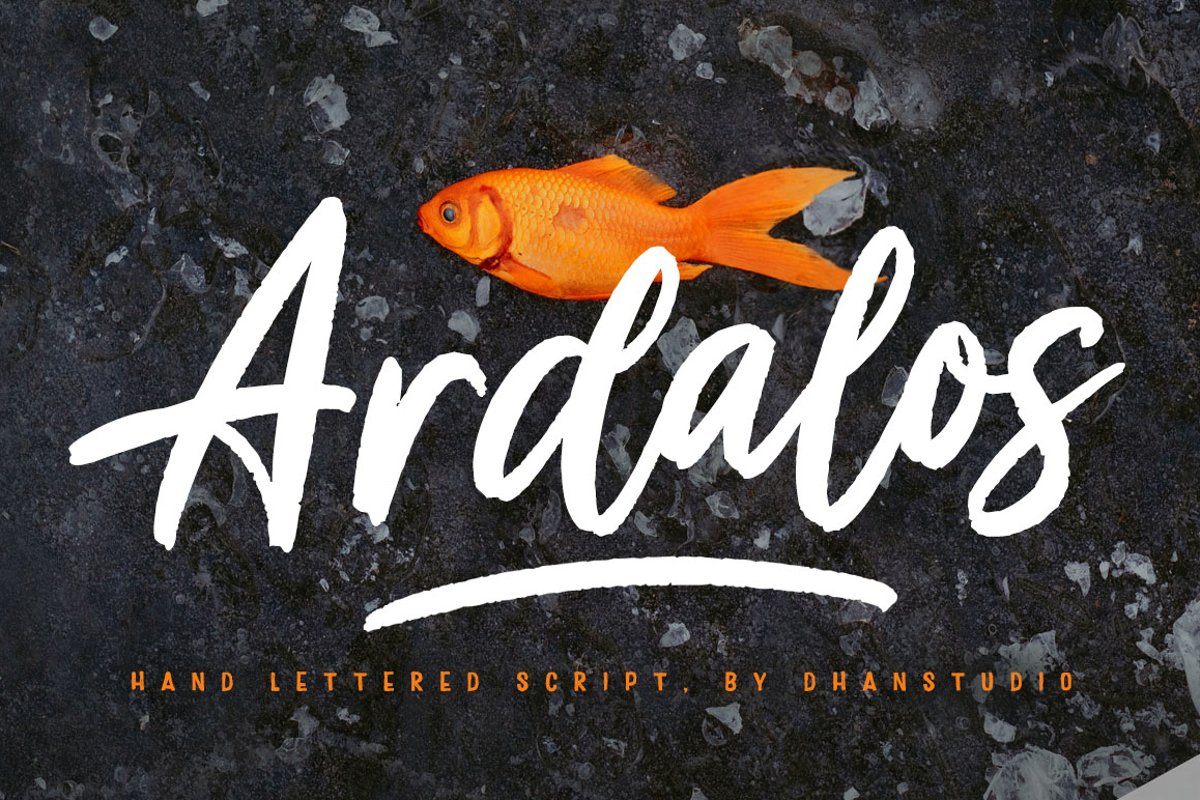
Ardalos
Ardalos Underlines
Ardalos
Ardalos adalah font kuas modern, pendekatan desain kontemporer, agak memiliki tekstur sedikit di tepi huruf dan font ini juga memiliki garis bawah yang membuat desain Anda lebih menarik.
Cocok untuk digunakan dalam desain judul seperti pakaian, undangan, buklet, desain alat tulis, kutipan, branding, logo, kartu ucapan, t-shirt, desain kemasan, poster dan banyak lagi.